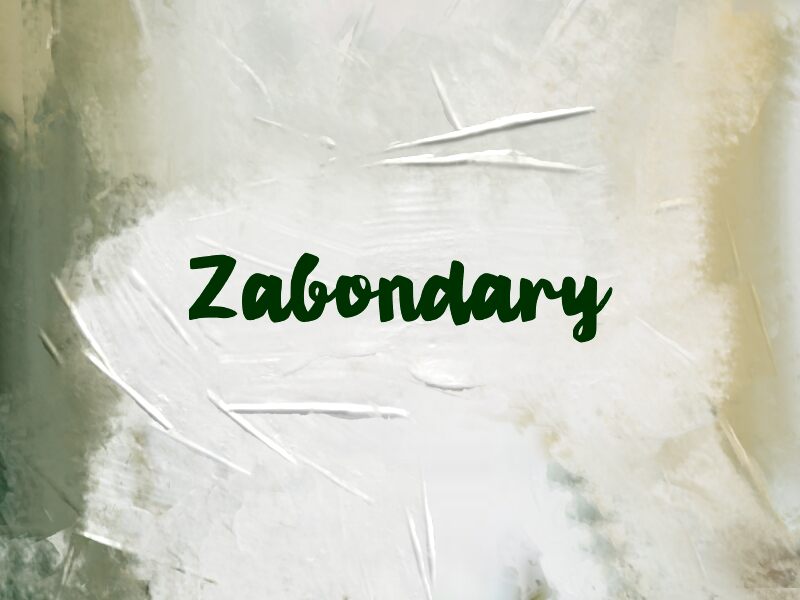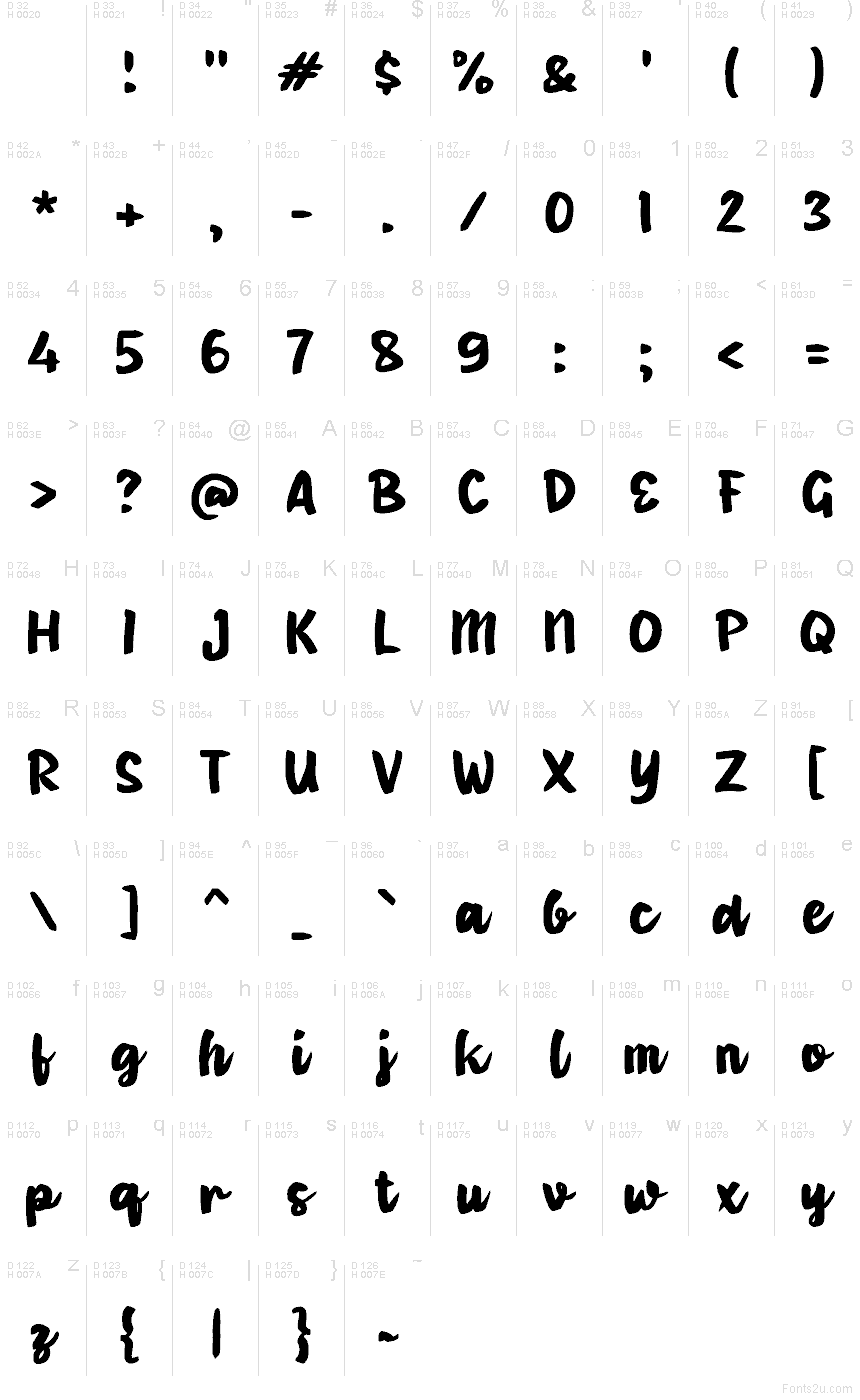
Zabondary
Zabondary от Wep — это бесплатный brush script шрифт с дерзким, живописным характером и непринужденным ритмом ручного письма. Буквы выглядят широкими и насыщенными, с округлыми соединениями, плотными штрихами и легкой «прыгучестью», которая придает словам живой, а не прилизанный вид.
Он отлично подходит для заголовков на плакатах, обложек альбомов, брендинга кофеен, графики в стиле стритвир и карточек для соцсетей, где бесплатному шрифту не хватает выразительности и движения. Используйте его для коротких фраз, логотипов или крупных цитат, если ищете эффект кисти, который выглядит быстро, весомо и немного небрежно.